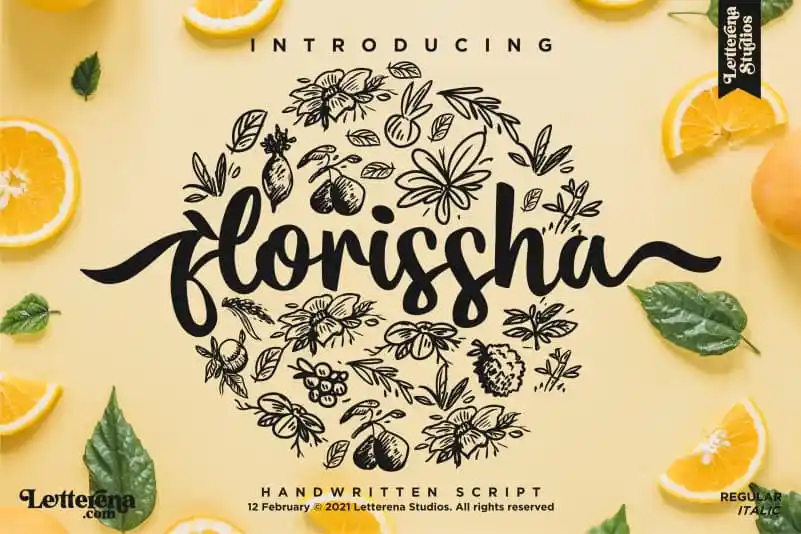
Descubra a elegância romântica da Florisha Script Font, perfeita para projetos diversos. Originada do laboratório de letras Letterenastudios, esta fonte script é ideal para criar um toque único e sofisticado em sua próxima obra. Seja para criar logos memoráveis, design de embalagens, arte para camisetas ou até mesmo capas de livro, Florisha Script traz uma harmonia perfeita à qualquer projeto. Seu charme elegante combina perfeitamente com um amplo espectro de aplicativos, incluindo identidades visuais de marcas, designs para cartões de visita e convites, cartazes e posters, design de embalagens personalizadas e até mesmo elementos fotográficos. Florisha Script também se destaca em projetos pessoais como assinaturas digitais e impressões digitais, dando um toque especial a eventos especiais. Seja você um criador de marca, designer ou qualquer pessoa que busca dar uma carinha única a seus trabalhos, esta fonte será uma escolha perfeita. Sua elegância natural e sua facilidade em ser aplicada tornam Florisha Script uma ótima adição à sua coleção de fontes script.